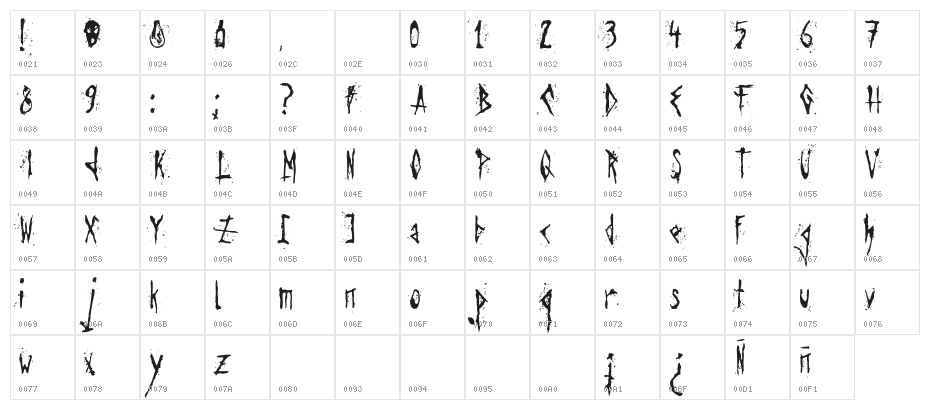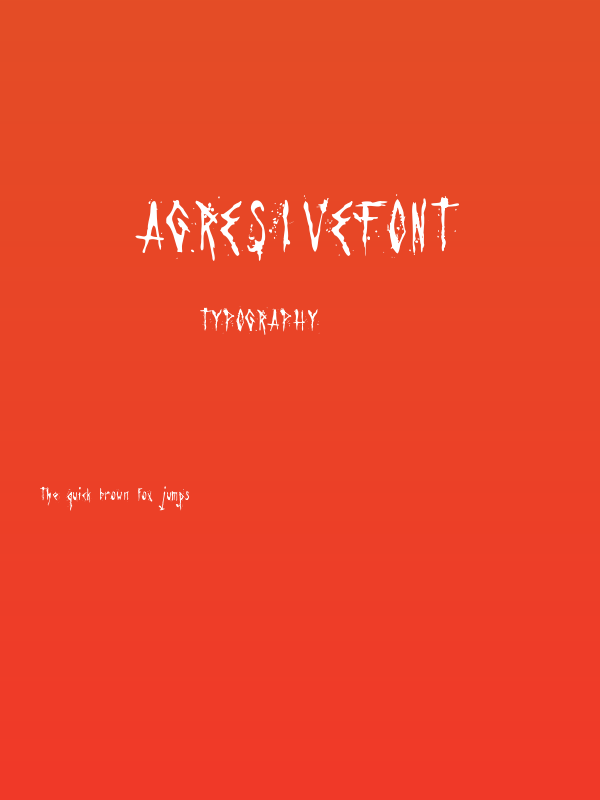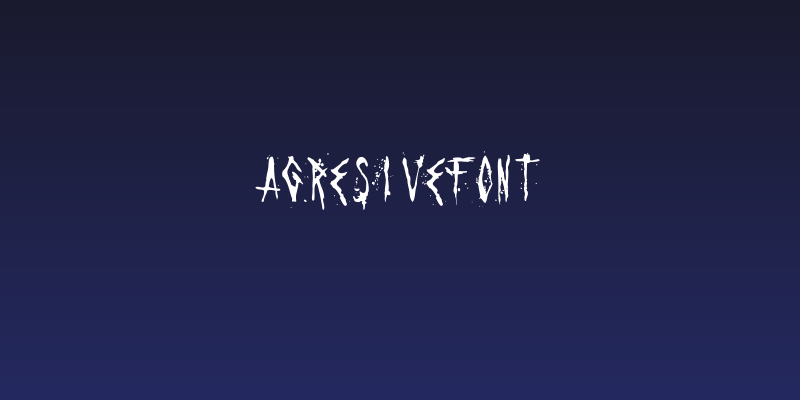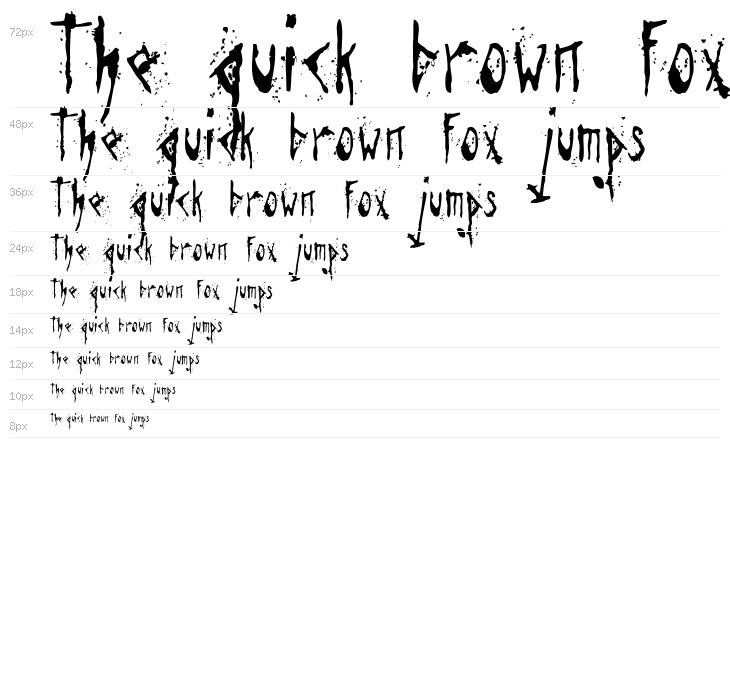
Agresivefont Font
✎ Script
| कंट्रास्ट | High |
| समग्र शैली | Grunge, Rebellious, Chaotic |
| उपयोग का मामला | Headlines, Logos, Posters |
| सुझाए गए प्रोजेक्ट | Album covers, horror movie posters, graffiti art, edgy branding, and rebellious-themed designs. |